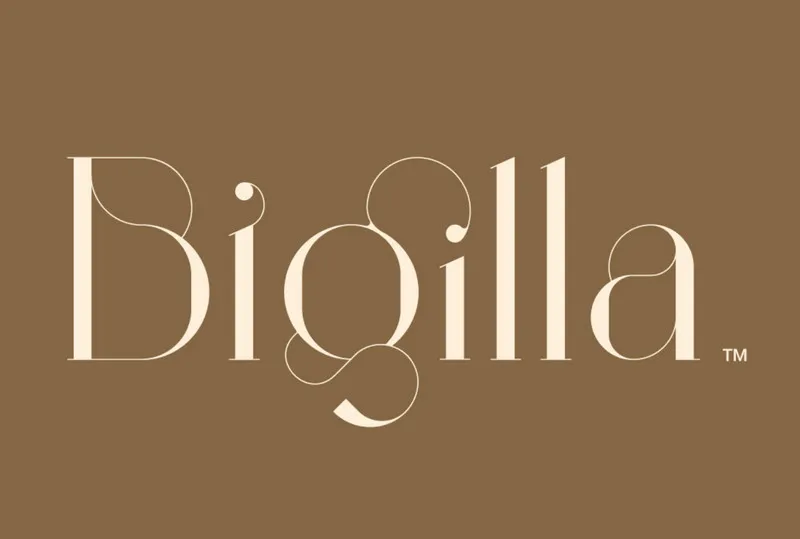
Bigilla™ Display Font – Download Grátis
A fonte Bigilla™ Display é uma novidade na categoria das tipografias para rótulos, projetada com alta contraste e alinhamento de traços sobrenaturais que incluem letras maiúsculas, números e símbolos diversos. Esta fonte é especialmente concebida como um tipo serifado ideal para uso em criações visuais, desde o branding até as capas de revistas ou embalagens de produtos. Com dois níveis de peso (Regular e Bold), a Bigilla™ Display oferece uma variedade de ligaturas e alternativas. Esta fonte é multilinguista, tornando-a perfeita para um amplo leque de aplicações em designs gráficos variados, incluindo marcas, outdoors, revistas e embalagens. Ela foi projetada para oferecer uma textura única que se destaca em qualquer aplicação visual onde deseja chamar a atenção do espectador com um design elegante e moderno.